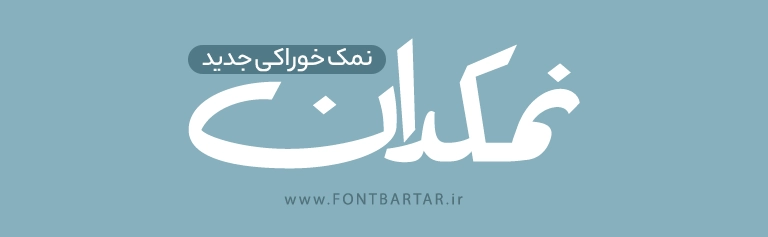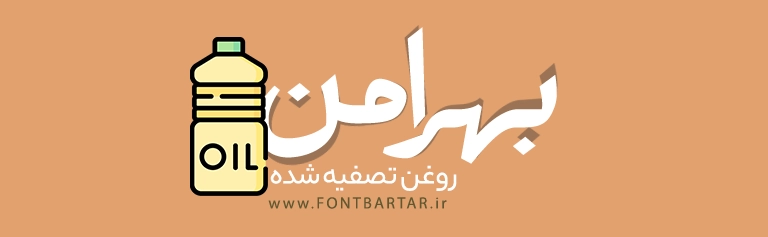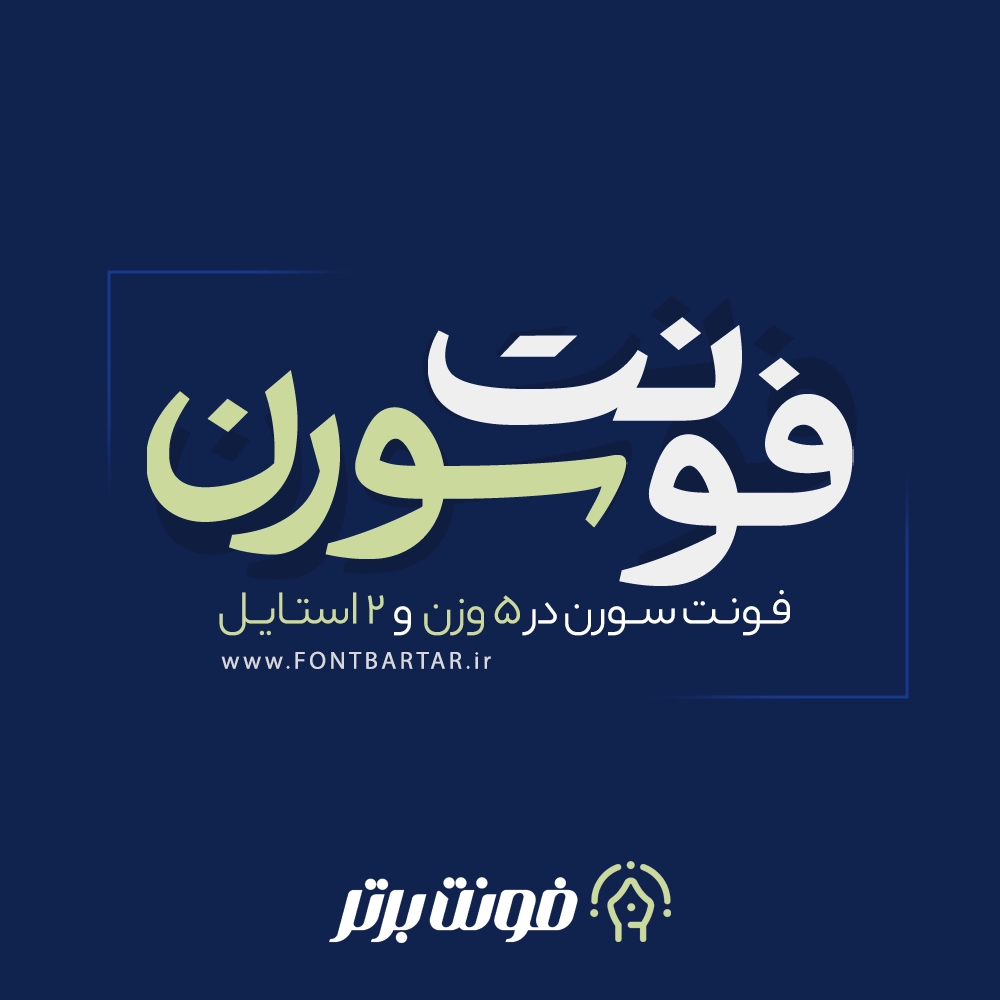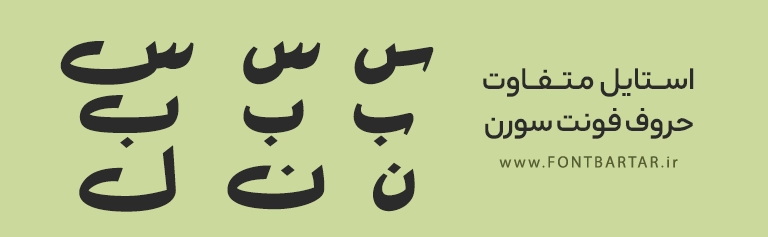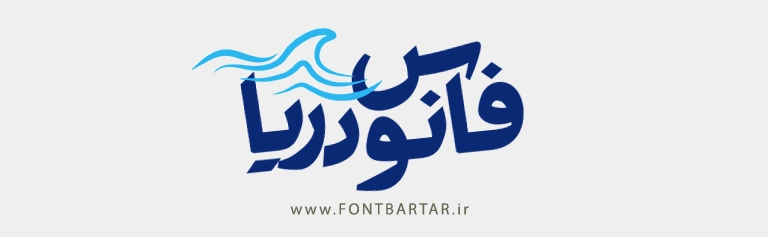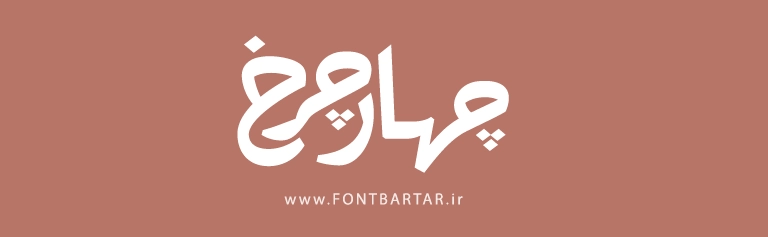
دانلود فونت سورن | فونت فارسی مدرن و حرفهای در ۵ وزن و ۲ استایل
✨ معرفی فونت زیبا سورن (Sooren Font)
فونت زیبا فارسی سورن یکی از جدیدترین و حرفهایترین فونتهای فارسی مدرن است که با طراحی منحصربهفرد، ظاهری ساده، خوانا و در عین حال زیبا ارائه میشود.
این فونت با هدف استفاده در طراحیهای گرافیکی، تبلیغاتی، چاپی و دیجیتالی ساخته شده و در ۵ وزن و ۲ استایل متفاوت عرضه شده است تا طراحان بتوانند در پروژههای مختلف از آن به راحتی استفاده کنند.
فونت سورن با الهام از سبکهای مینیمال و تایپوگرافی مدرن، انتخابی عالی برای طراحان حرفهای، برندها و تولیدکنندگان محتوا است که به دنبال یک فونت خاص، رسمی و انعطافپذیر هستند.
🎨 ویژگیهای منحصربهفرد فونت فارسی سورن
- 📦 دارای ۵ وزن (لایت تا بولد) و ۲ استایل حروف فونت زیبا
- 🖋️ خرید فونت زیبا پشتیبانی کامل از حروف فارسی و عربی
- 💻 مناسب برای استفاده در طراحی لوگوتایپ، پوستر، بنر، سایت و رابط کاربری
- 📱 بهینهشده برای استفاده در موبایل و صفحات وب
- 🔤 طراحی نرم و چشمنواز برای متون طولانی و تبلیغاتی
چرا بهترین فونت زیبا انتخاب طراحان حرفهای است؟
فونت زیبا سورن با ترکیب بینظیر زیبایی و خوانایی، جایگاه ویژهای بین فونتهای فارسی جدید پیدا کرده است، این فونت برای طراحی لوگو، نوشتههای تبلیغاتی و صفحات وب بسیار ایدهآل است و در هر سایزی وضوح بالا و تعادل بصری فوقالعادهای دارد.
💡 کاربردهای فونت زیبا جدید در طراحی
فونت سورن یک فونت چندمنظوره و زیبا است که برای طیف وسیعی از کاربردها مناسب میباشد، از جمله:
- طراحی بنرهای تبلیغاتی و دیجیتال مارکتینگ
- ساخت لوگوتایپ و تایپوگرافی برندها
- فونت زیبا برای استوری
- فونت زیبا برای اینشات
- طراحی کاور پستهای اینستاگرام
- استفاده در طراحی رابط کاربری (UI/UX)
- تولید محتوای گرافیکی برای وبسایتها
❓ سوالات متداول فونت زیبا سورن (FAQ)
2. فونت زیبا برای استوری برای چه نوع طراحیهایی مناسب است؟
فونت زیبا سورن برای طراحی لوگو، پوستر، وبسایت، بنر تبلیغاتی و تایپوگرافی ایدهآل است.